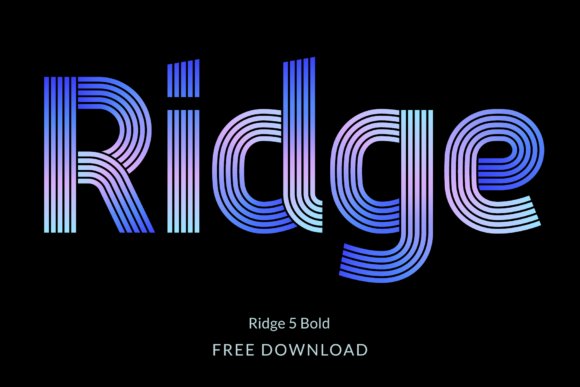
Ridge 5 Bold
Encontrar los elementos de diseño adecuados puede ser un desafío, pero Ridge 5 Bold ofrece una colección excepcional que eleva tu trabajo al instante.